あざとい!「小悪魔」な雰囲気にぴったりな日本語フォント
かわいいだけでは少し物足りない。甘さの中に、ちょっとした毒っ気や、わざとらしいくらいの可愛さを入れたいときに便利なのが「小悪魔」な雰囲気のフォントです。丸くてガーリーな文字、ツノや棘のような装飾がある文字、平成ギャルっぽいクセのある文字など、選ぶフォントによって印象は大きく変わります。
今回は、あざとカワイイ世界観に合わせやすい日本語フリーフォントをピックアップしました。ゴスロリ、地雷系、ハロウィン、推し活、恋愛系サムネイル、SNS投稿など、甘さと小さな危うさを両方出したいデザインに使いやすいフォントを紹介します。
あざとカワイイ小悪魔系フォントまとめ
サマサン・ドノクン
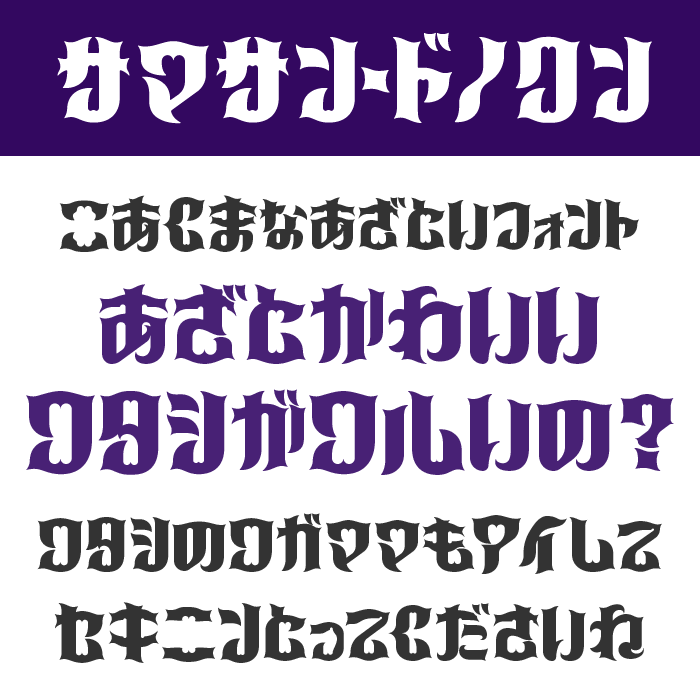
| 使用用途 | 見出し/タイトルロゴ/ハロウィン系デザイン |
| おすすめの世界観 | 小悪魔/ゴシックポップ/ハロウィン/毒かわいい/ダークファンタジー |
サマサン・ドノクンは、文字の先端にツノや牙のような鋭さを感じる、インパクトの強いデザインフォントです。
太くどっしりした形の中に、不規則な切り込みや装飾が入り、かわいいだけでは終わらないクセの強さがあります。小悪魔っぽいテーマでは、いたずらっぽさや少し危ない雰囲気を前面に出したいときにぴったり。ハロウィン、魔女、ダーク系のロゴ、個性的なサムネイルなどで主役にしやすいフォントです。
めもわーる
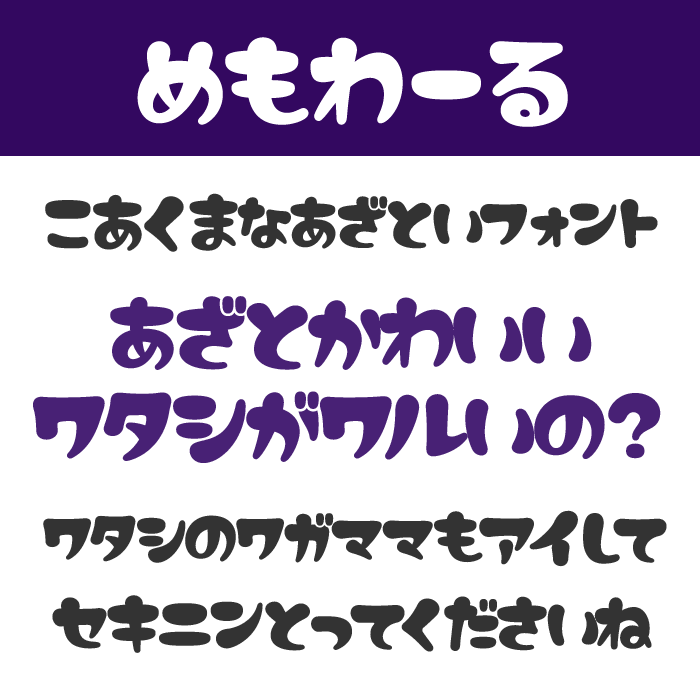
| 使用用途 | 見出し/タイトルロゴ/レトロポップ |
| おすすめの世界観 | あざとかわいい/レトロガーリー/ファンシー/お菓子/雑貨 |
めもわーるは、丸みのある太い文字に、レトロでファンシーな可愛さを詰め込んだフォントです。
ころんとした形で親しみやすいのに、少し大げさなシルエットがあり、ただの可愛い文字よりも印象に残ります。小悪魔テーマでは、甘く見せながらちゃっかり目立つ「あざとさ」を出したいときにぴったり。お菓子のパッケージ、ガーリーなバナー、推し活系のタイトルなど、可愛さを強めたい場面に向いています。
デビルのしっぽ
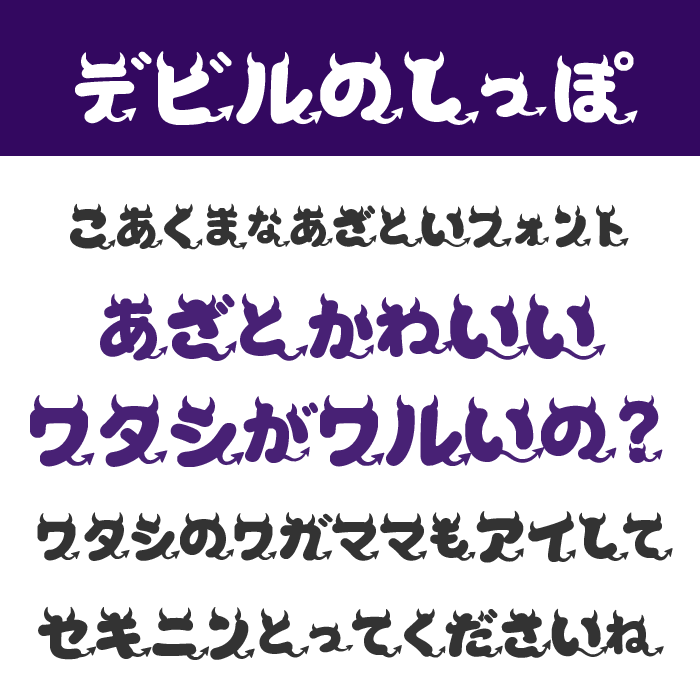
| 使用用途 | 見出し/タイトルロゴ/キャラクター系デザイン |
| おすすめの世界観 | 小悪魔/ツノ/しっぽ/ハロウィン/いたずらっ子/毒かわいい |
デビルのしっぽは、文字のあちこちに小さなツノやしっぽのような装飾が入った、小悪魔感たっぷりのフォントです。
丸みのある可愛らしい骨格に、ちょこんと尖ったパーツが加わることで、甘さの中にいたずらっぽい表情が生まれています。あざとカワイイ雰囲気を出すなら、セリフ調の見出しやキャラクター名に使うのがおすすめ。ハロウィン、魔法少女、ダークかわいいSNS画像にもよく合います。
大大大大だぁい好き
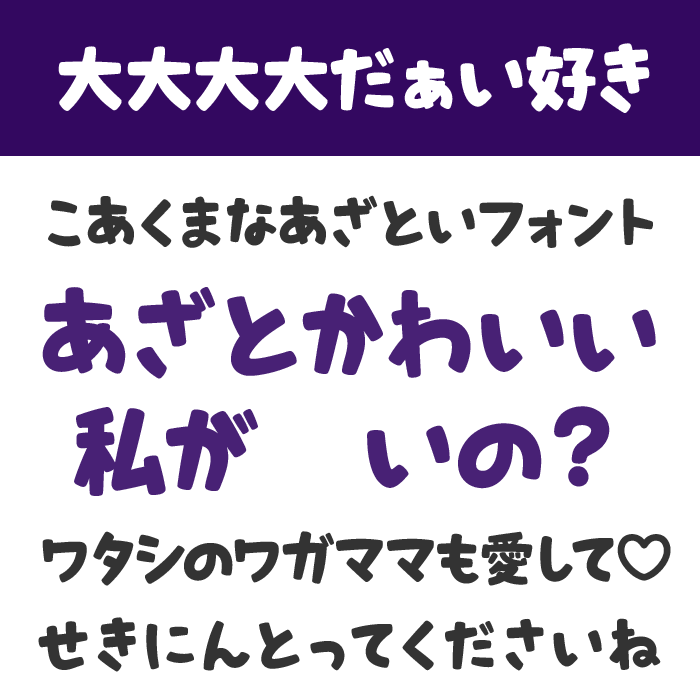
| 使用用途 | 見出し/タイトルロゴ/うちわ文字/推し活 |
| おすすめの世界観 | あざとい告白/推し活/量産型/地雷系/恋愛バナー/甘めポップ |
大大大大だぁい好きは、手書きの勢いと大きな感情がそのまま文字になったような、元気で可愛いフォントです。
太さや傾きに少しラフさがあり、まっすぐすぎないところが魅力。小悪魔テーマでは、「私のこと好きでしょ?」と甘く迫るような、少しわがままで可愛いニュアンスを作れます。推し活うちわ、恋愛系サムネイル、ガーリーな告知画像など、感情を大きく見せたいデザインにぴったりです。
ぎゃる文字ゴシック
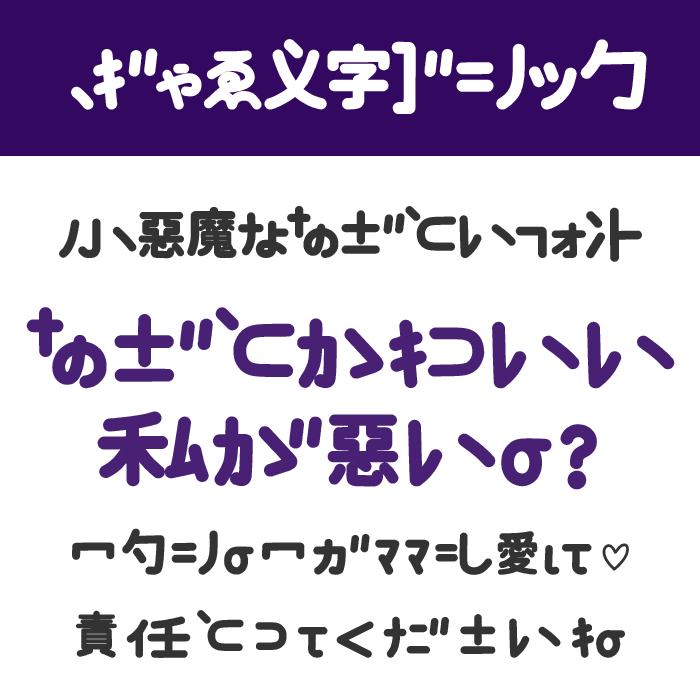
| 使用用途 | 見出し/タイトルロゴ/ギャル系デザイン |
| おすすめの世界観 | ギャル/あざとかわいい/平成レトロ/地雷系/SNSサムネイル |
ぎゃる文字ゴシックは、丸ゴシックの読みやすさに、ギャル文字のようなクセを少し混ぜた可愛いフォントです。
文字の一部が大胆に省略されたり、記号っぽく見えたりするため、普通のゴシック体よりもぐっと個性的に見えます。小悪魔テーマでは、強気だけど可愛い、少し挑発的な雰囲気を出したいときに相性抜群。平成ギャル、量産型、地雷系、推し活画像など、テンション高めのデザインに使いやすいフォントです。
ひょうきんな!?ポップ体
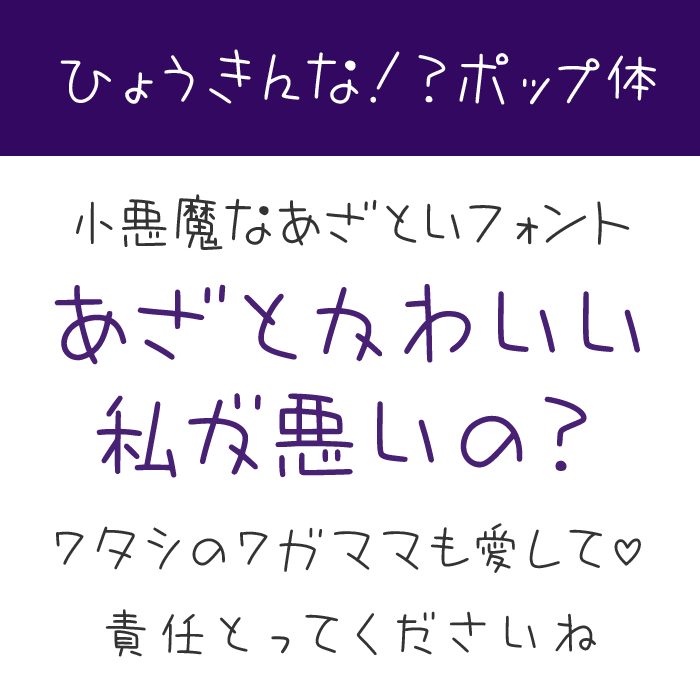
| 使用用途 | 見出し/本文/タイトルロゴ/手書きPOP |
| おすすめの世界観 | ゆるい小悪魔/手書きPOP/平成バラエティ/抜け感/コミカル |
ひょうきんな!?ポップ体は、80年代のテレビ番組で使われていそうな手書き文字をイメージした、ゆるく楽しいポップ体です。
細めの線と少し不安定な字形が、きっちりしすぎない親しみやすさを作っています。小悪魔テーマでは、怖さよりも「からかってくる可愛さ」や、わざとらしい甘えの雰囲気を出したいときにぴったり。セリフ風の画像、ゆるい告知、コミカルなバナーに使うと、軽い毒っ気が出せます。
はちまるポップ
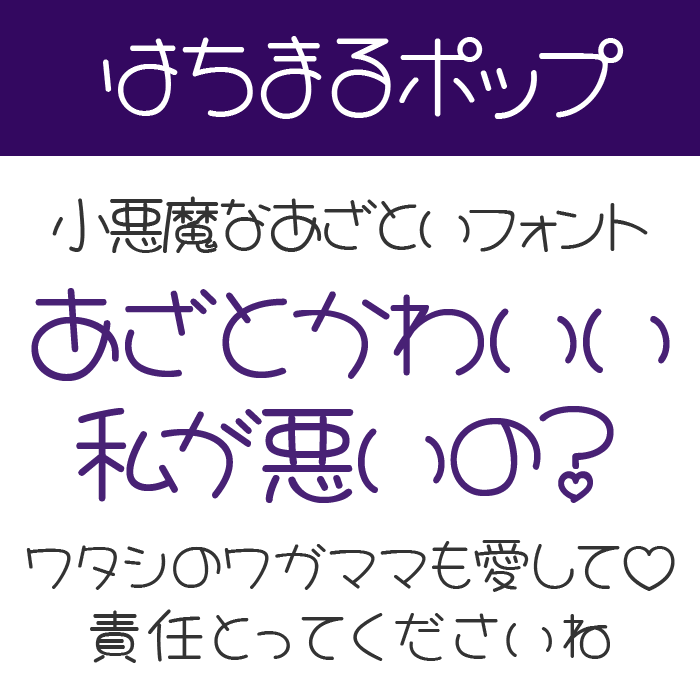
| 使用用途 | 見出し/本文/タイトルロゴ |
| おすすめの世界観 | 平成レトロ/丸文字/少女漫画/あざとかわいい/ガーリー |
はちまるポップは、80〜90年代の丸文字を現代風に整えた、レトロで可愛い日本語フォントです。
線は細めですが、文字全体に丸みがあり、やわらかく軽やかな印象を作れます。小悪魔テーマでは、強い毒気よりも、少女漫画のヒロインのようなあざとさや、計算された可愛さを出したいときに向いています。SNSの一言画像、ガーリーな見出し、恋愛系コンテンツのタイトルなどに使うと、甘さのある雰囲気に仕上がります。
ぽっぷまる
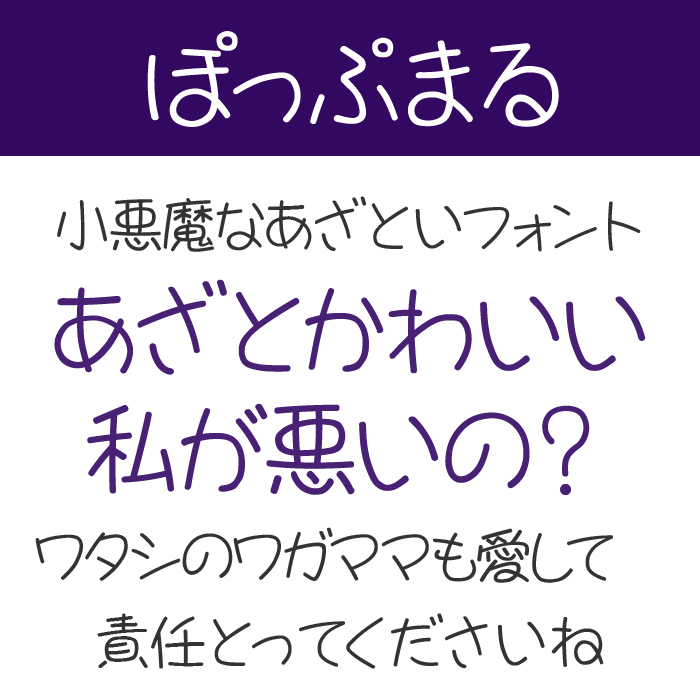
| 使用用途 | 見出し/タイトルロゴ/手書き風デザイン |
| おすすめの世界観 | 丸文字/あざとかわいい/平成レトロ/手書き感/女の子向け |
ぽっぷまるは、手書き文字のような自由な動きと、丸文字らしい可愛さを持つフォントです。
文字の線がきれいに整いすぎていないため、自然に書いたメモのような親しみやすさがあります。小悪魔テーマでは、さらっと可愛いことを言って相手を振り回すような、抜け感のあるあざとさを表現しやすいフォントです。ガーリーなバナー、手書き風のサムネイル、恋愛系の短いコピーなどに向いています。
JK丸ゴシック
| 使用用途 | 見出し/本文/タイトルロゴ |
| おすすめの世界観 | 女子高生風/小ぶりで可愛い/清楚系小悪魔/SNS投稿/恋愛テキスト |
JK丸ゴシックは、女子高生の文字をイメージしたJKゴシックに丸みを加えた、こぶりで可愛い丸ゴシック体です。
クセは強すぎず、本文にも使いやすい読みやすさがあります。小悪魔テーマでは、派手に主張するよりも、さりげなく可愛い言葉で相手を引き寄せるような雰囲気にぴったり。恋愛系の記事画像、SNS投稿、吹き出し、プロフィール風デザインなど、自然なあざとさを出したい場面で使いやすいフォントです。
黒薔薇ゴシック
| 使用用途 | 見出し/タイトルロゴ/ゴシック系デザイン |
| おすすめの世界観 | ゴスロリ/黒薔薇/ダークロマン/小悪魔/毒かわいい/耽美 |
黒薔薇ゴシックは、ゴシック体をベースに、薔薇の棘のような装飾を加えたエレガントなデザインフォントです。
骨格は読みやすく整っていますが、先端に鋭さがあるため、上品さと危うさが同時に感じられます。小悪魔テーマでは、可愛いだけでは物足りない、少しミステリアスで高貴な雰囲気を出したいときにぴったり。ゴスロリ、ハロウィン、ダークファンタジー、推し活の黒系デザインに映えるフォントです。
モフ字
| 使用用途 | 見出し/本文/タイトルロゴ |
| おすすめの世界観 | ゆるい小悪魔/モフモフ/毒かわいい/手書きPOP/不思議かわいい |
モフ字は、角のない曲線だけで作られた、モフモフとした質感が楽しいデザインフォントです。
線に不規則な揺らぎがあり、少し読みにくい字も含めて、独特の味として楽しめます。小悪魔テーマでは、怖さよりも、得体の知れない可愛さや、いたずら好きなキャラクター感を出したいときにおすすめ。ゆるいハロウィン画像、手書きPOP、雑貨風デザインなど、クセのある可愛さを添えたい場面に合います。